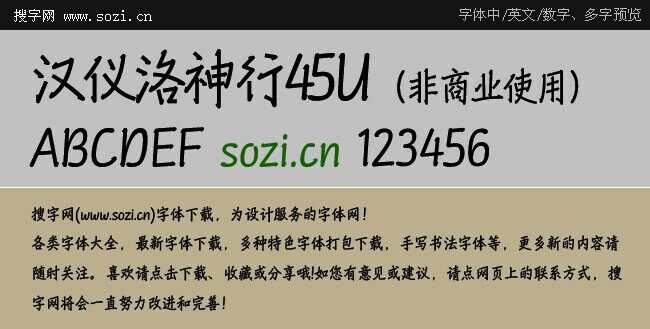
漢儀洛神行45U
搜字網(wǎng)給大家提供一款漢儀洛神行45U中文字體下載,漢儀洛神行取意趙孟頫行書《洛神賦》卷,行中兼楷,在字形結(jié)構(gòu)上尋求“竦輕軀以鶴立,若將飛而未翔”的意境,結(jié)合現(xiàn)代等線的筆畫設(shè)計(jì),保留行楷的流暢瀟灑而減弱古舊氣息。漢儀洛神行的字形偏長,中宮略小而筆畫舒展,挺拔如鶴立。重心平穩(wěn),字形略帶書寫的自然傾斜,呈現(xiàn)“若將飛而未翔”之勢(shì)。適用于畫冊(cè)設(shè)計(jì)、海報(bào)設(shè)計(jì)、包裝設(shè)計(jì)等場合使用。(本字體為個(gè)人非商用版,如需要商用請(qǐng)聯(lián)系漢儀公司購買版權(quán))